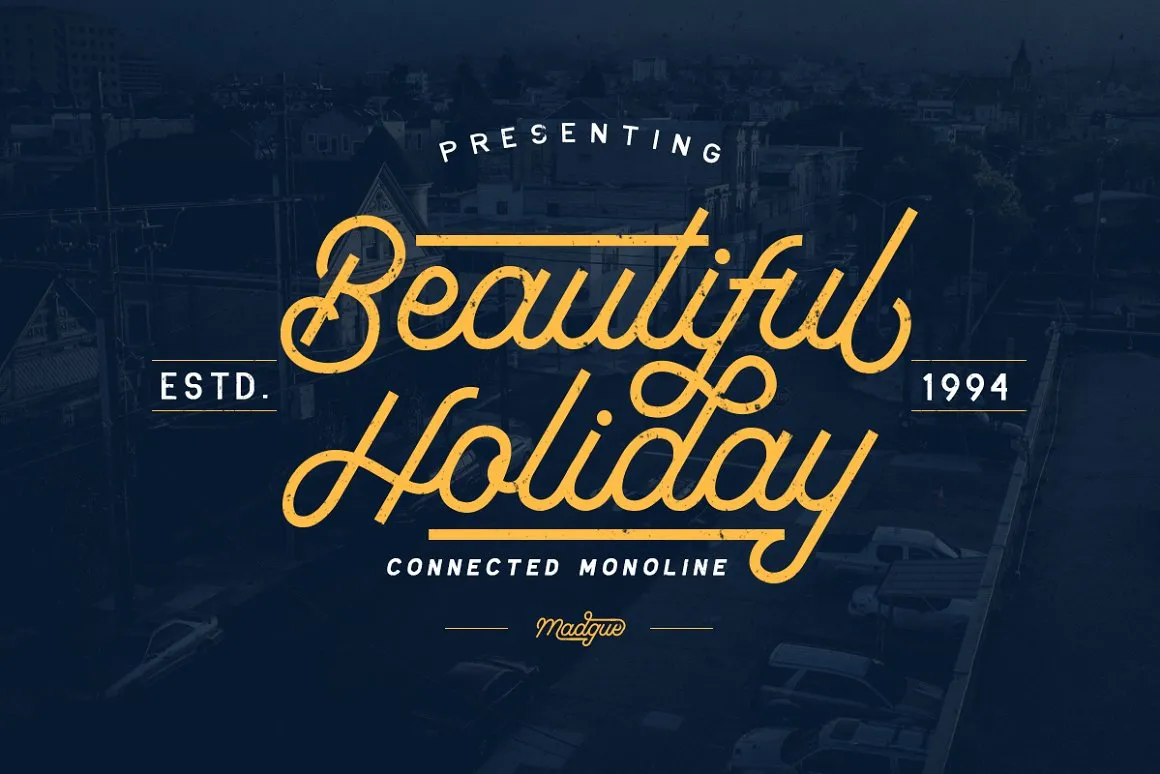
Descubra uma nova opção para seus projetos criativos com a Madgue Script Font, uma escolha exclusiva entre os Blackletter Fonts disponíveis no mercado. Desenvolvida por Sarid Ezra e lançada pela 178-MC, esta fonte premium é um dos destaques da Creativemarket. Madgue oferece uma experiência única, com sua singularidade monoline que vai além das limitações convencionais do tipo de letra. Suas ligaturas sofisticadas e alternativas estilizadas garantem texturas vibrantes e variedade em cada projeto. O suporte a múltiplas línguas é um detalhe adicional que faz desta fonte uma ferramenta versátil. Para designers, artistas digitais ou qualquer profissional de comunicação visual, a Madgue Script Font se destaca como uma escolha ideal para criar logomarcas memoráveis. Com seu estilo único e recursos únicos incorporados, você pode transformar simples ideias em elementos visuais impactantes. Não perca mais tempo com fontes convencionais – experimente a Madgue Script Font hoje e descubra o potencial real de sua criatividade.